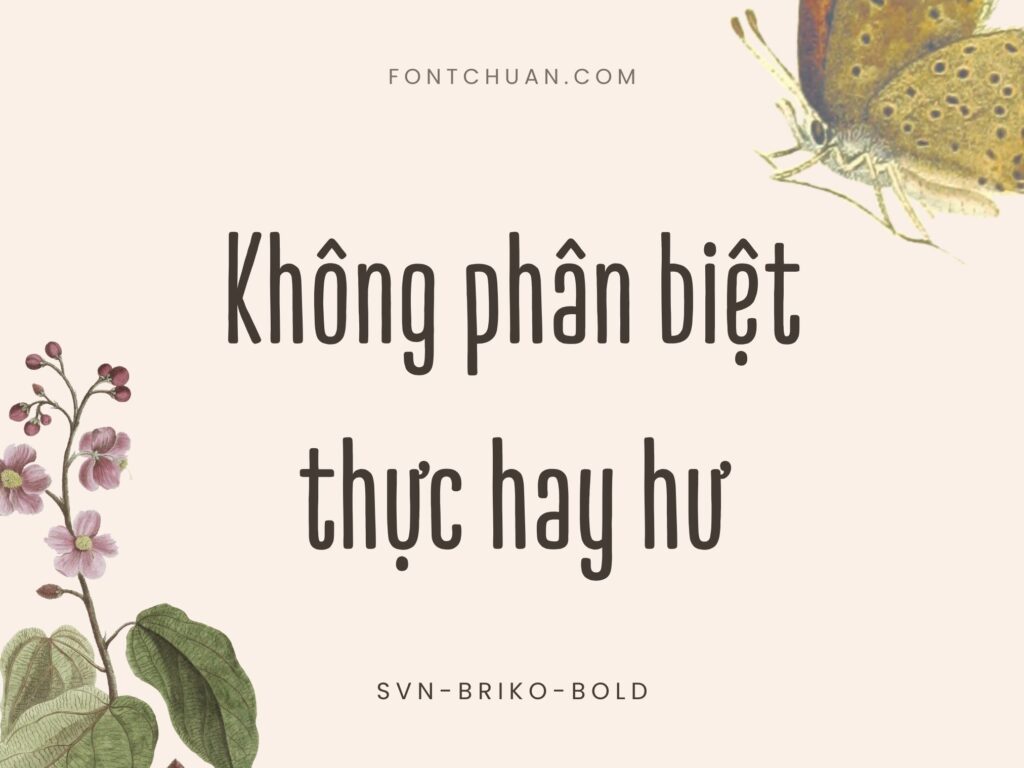
Font SVN Briko Bold Việt Hóa
Tác giả Font: Paul Chen
Font SVN Briko Bold là phiên bản Việt hóa của kiểu chữ Briko Bold, được thực hiện bởi Styleno.1 Fonts. Briko Bold là một kiểu chữ sans-serif hiện đại, nổi bật với các đường nét đậm và góc cạnh, tạo cảm giác mạnh mẽ và năng động. Font này thích hợp cho nhiều mục đích sử dụng khác nhau, từ thiết kế logo, tiêu đề đến các ấn phẩm quảng cáo.
SVN Briko Bold lý tưởng cho các dự án thiết kế yêu cầu sự nổi bật và cá tính, như thiết kế logo, tiêu đề, bao bì sản phẩm và các ấn phẩm quảng cáo. Các ngành nghề như quảng cáo, công nghệ và bất động sản có thể tận dụng font này để tạo điểm nhấn trong thiết kế. Ngoài ra, font cũng thích hợp cho các sự kiện như Tết, Giáng sinh, Valentine và các lễ hội khác.